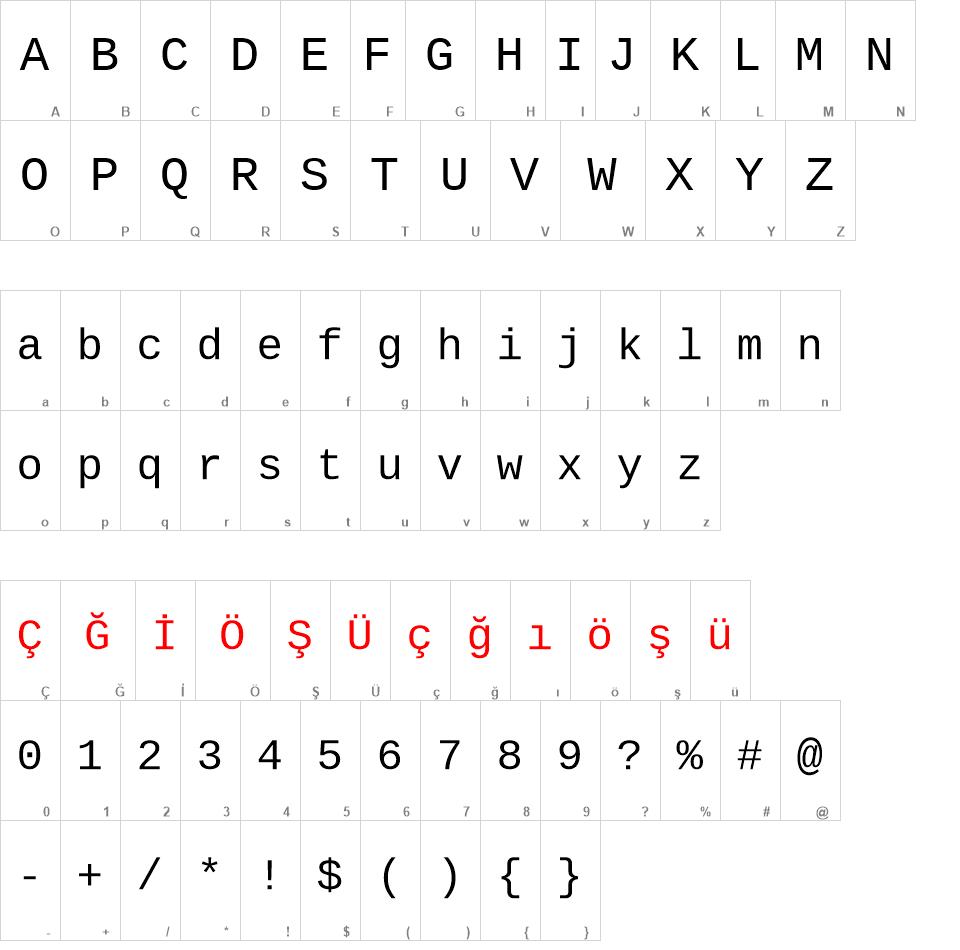
Cousine
Cousine  font
Cousine wurde von Steve Matteson als innovatives, erfrischendes serifenloses Design entworfen, das mit Courier New ™ kompatibel ist. Die Cousine-Schriftart bietet eine erweiterte Anzeigelesbarkeit und den paneuropäischen WGL-Zeichensatz und erfüllt die Anforderungen von Entwicklern, die nach breitenkompatiblen Schriftarten suchen, die die Übertragbarkeit von Dokumenten zwischen Plattformen ermöglichen.